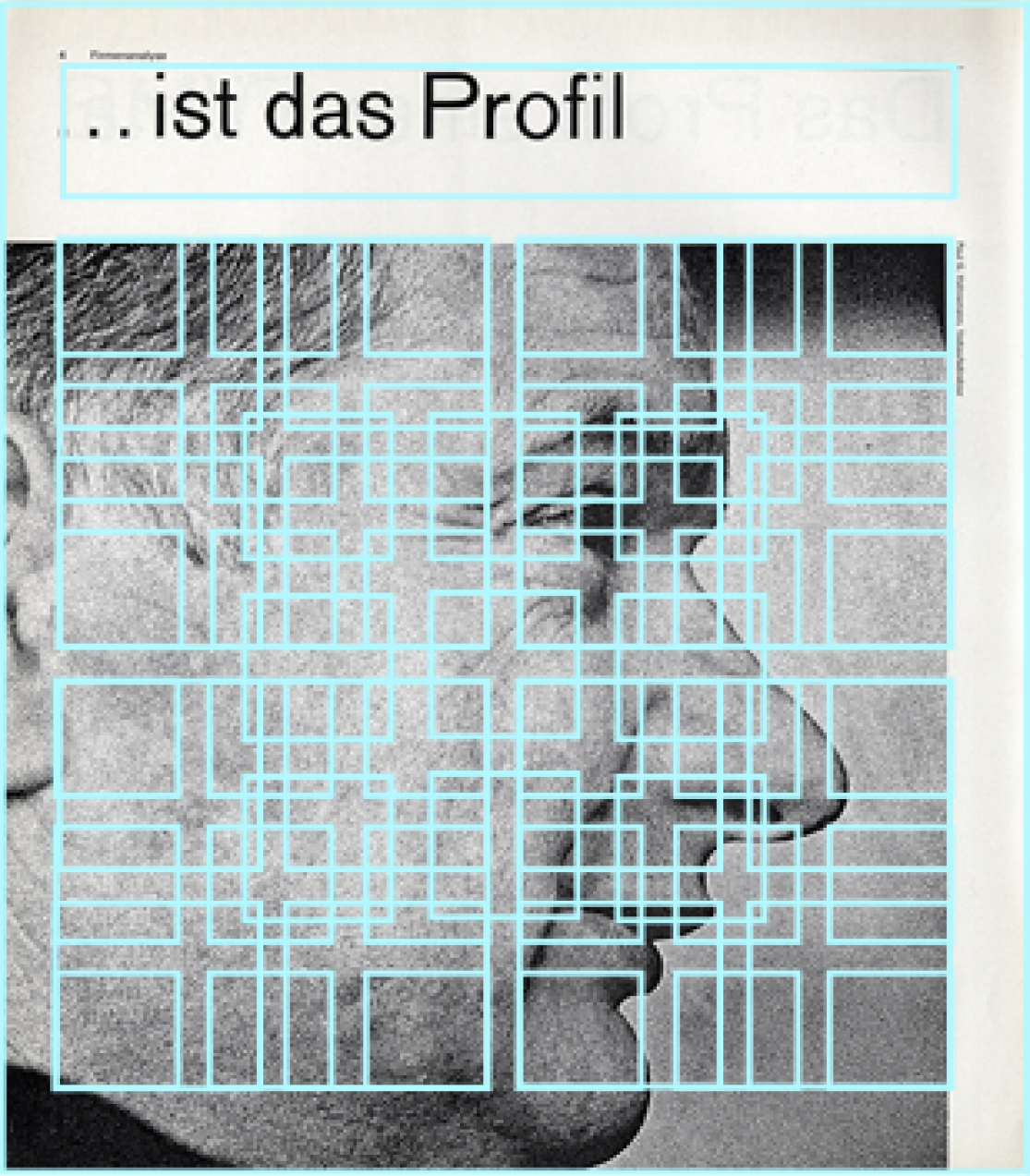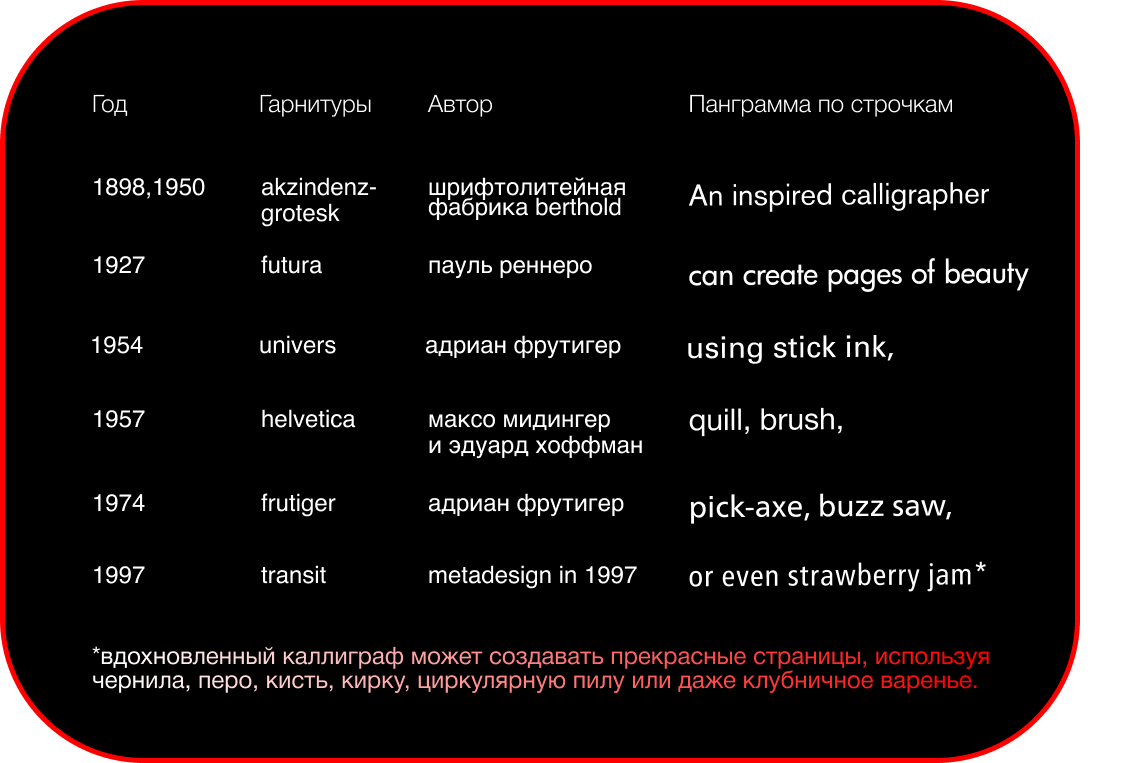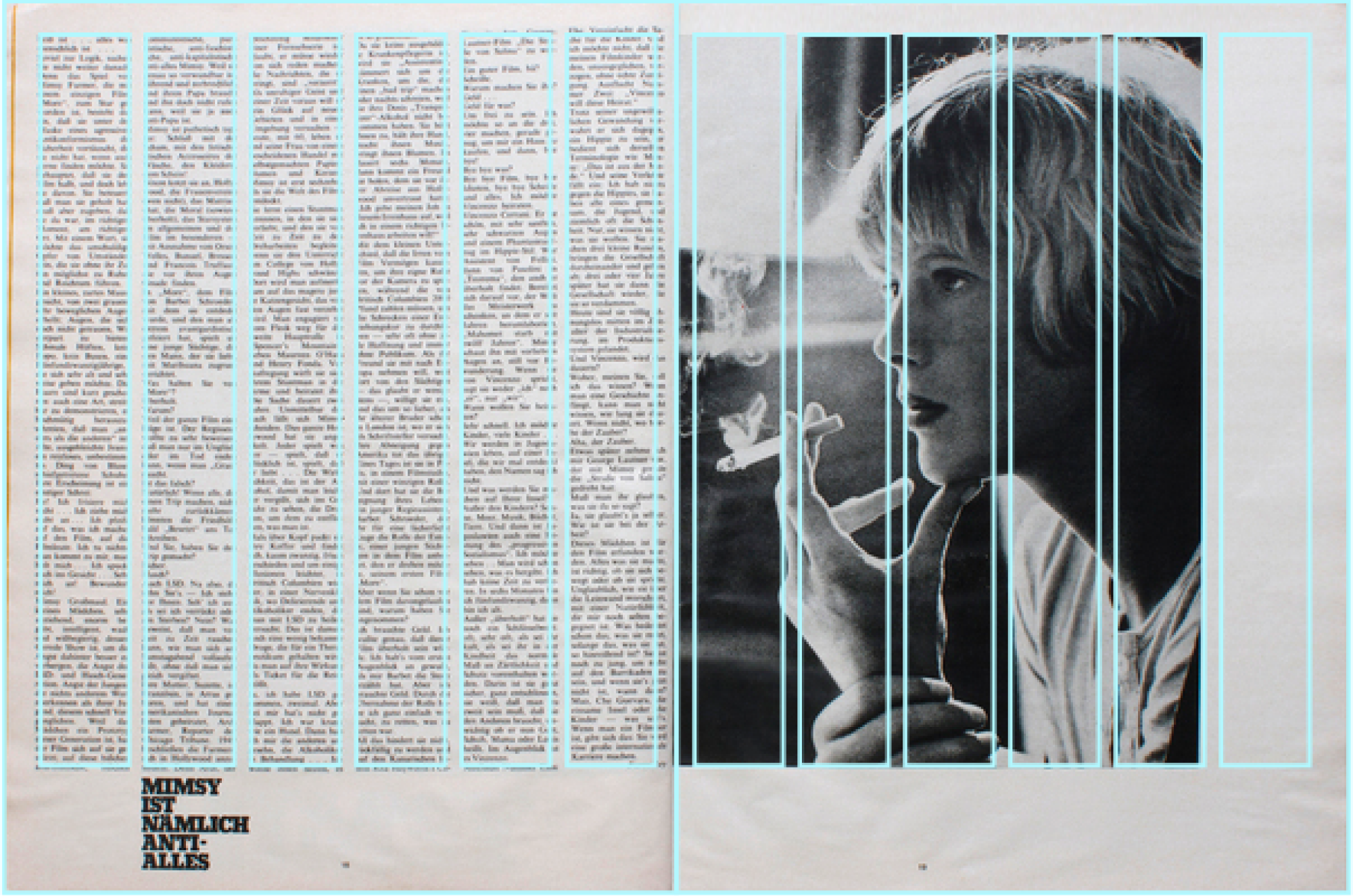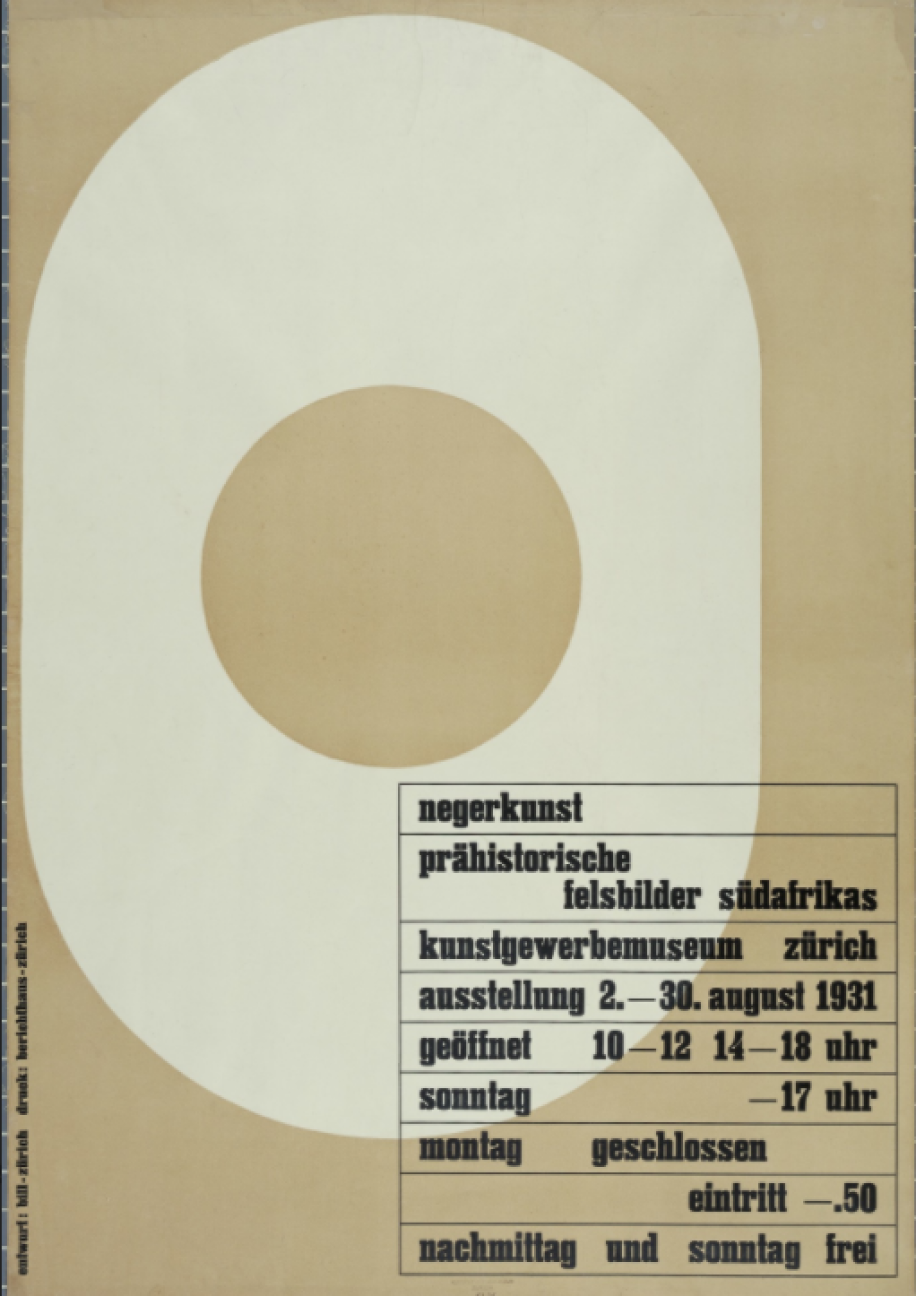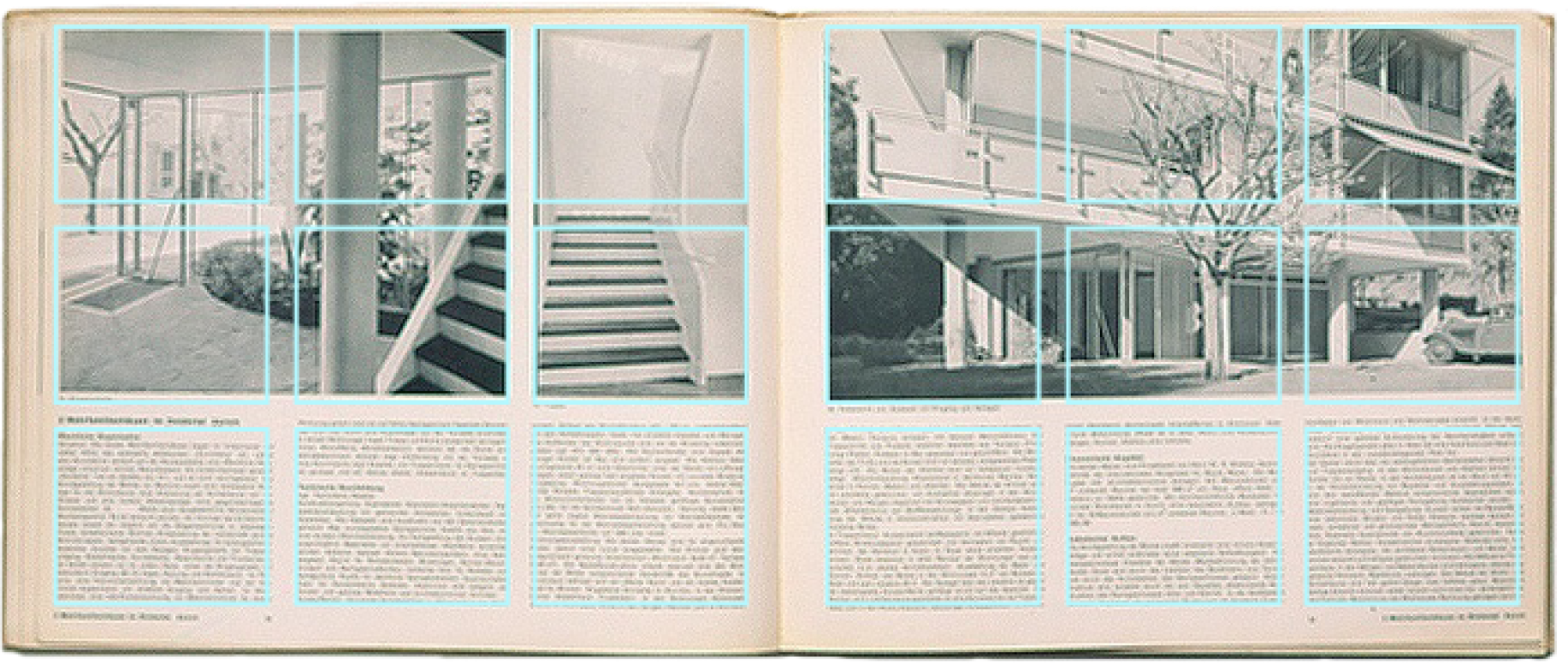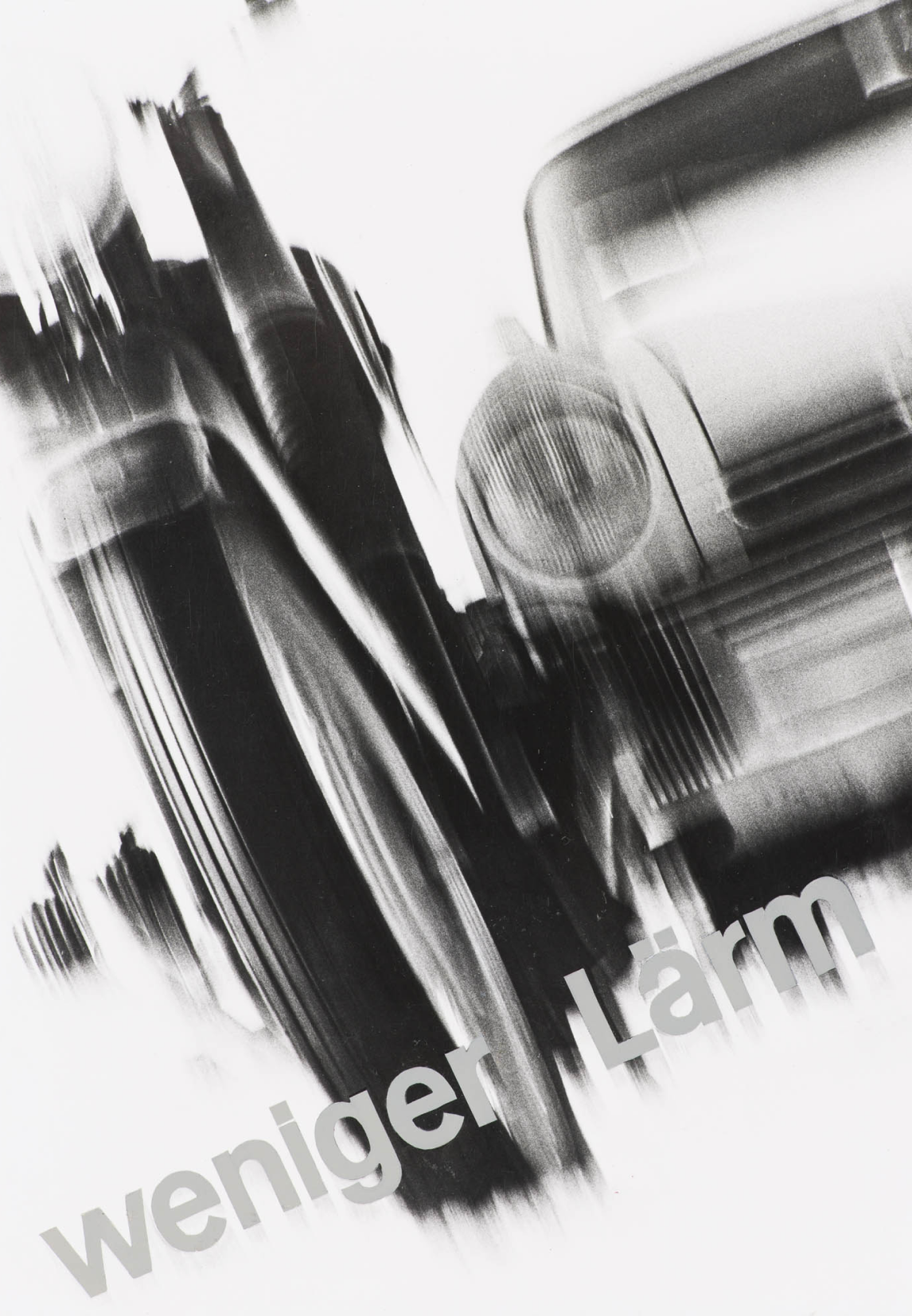
анатомия плаката
в швейцарском стиле
швейцарский стиль или международный стиль, относится к движению, которое зародилось в России, Нидерландах
и Германии во время 1920-х и 30-х годов.
затем дизайнеры возглавили движениев 1950-х годах в Швейцарии.
дизайнер Юлия
благодаря нейтралитету своей
страны во время войны швейцарские художники имели возможность плодотворно работать.
основатель швейцарской школы— Ян Чихольд.(1902-1974)
год рождения швейцарского стиля: 1927 г.
форма следует за функцией — это принцип, связанный с модернистской архитектурой 20-го века и промышленным дизайном.
Луис Генри Салливан — американский архитектор, первопроходец рационализма, отец американского модернизма.
баухауз всегда поддерживал функциональный стиль, все вещи,
которые там создавались, были понятны, точны и позволяли людям более успешно взаимодейстоввать
со средой.
это создание единого стиля, способного обеспечить нужды архитектуры, графического и предметного дизайна,
моды и искусства.
решение абстракция — художественный прием, который изучал и практиковал
Пит Мондриан.
основной проблематикой конструктивизма было взаимодействие реального и абстрактного.
вывел принципы новой типографики, которые легли в основу швейцарского дизайна.
«новая типографика. руководство для современного дизайнера»
1928
автор известной книги
«Типографика»
1967
журнал Эмиля Рудера «Шрифт»
часто считают, что он произвел наиболее «решающее влияние на швейцарский графический дизайн».
некоторые из учеников Келлера стали лидерами в создании Международного движения типографского стиля.
геометрия
философский смысл
работа с цветом
Эрнест Келлер,
постер для выставки, 1931.
«Модульные системы в графическом дизайне.» Пособие для графиков, типографов и оформителей выставок
Йозеф Мюллер-Брокман
Работа над сеткой и шрифтом Akzindenz-Grotesk.
сетка - это помощь,
а не гарантия
(иозеф-мюллер брокман)
сетки помогают удерживать внимание читателя, повышают качество восприятия текста.
простейшая сетка, которая легла в основу модульной системы, состояла из квадратов.
она начала использоваться уже в конце первой четверти ХХ века.
в этой книге макс билл применил деление страницы на девять горизонтальных модулей.
они позволили свободно располагать иллюстрации и размещать на них текст на трех языках.
макс билл, «Die Neue Architektur», 1940 г.
билл использовал шестимодульную сетку в своем знаменитом плакате «Negerkunst»,
в 1931 году.
многослойная сетка карла герстнера
эта сетка также дает возможность выбрать шесть, четыре, три или две колонки, но в придачу предусматривает еще и возможность оригинального пятиколонного макета.
фактически она представляет собой шестиколонник с наложенным на него четырехколонником.
12-колоночная сетка вилли флекхауза
журнал «Twen», февраль 1970 г.
фотография была не способом создания картинок, а возможностью расширить восприятие мира.
ласло мохой-надь «парусный спорт (хильда хорн)», 1928
ласло мохой-надь«сестры олли и долли», 1925
предпочтение иллюстрациям фотографий, как изображений, отражающих реальную действительность и факты.
процесс создания
«weniger lärm» 1960
йозеф-мюллер брокман
также занимался фотографией.
минимализм в цвете:
текст должен быть черным, фон — ярким или светлым.
цвет забирает внимание и направляет его на черный текст, который в свою очередь доносит необходимую информацию.